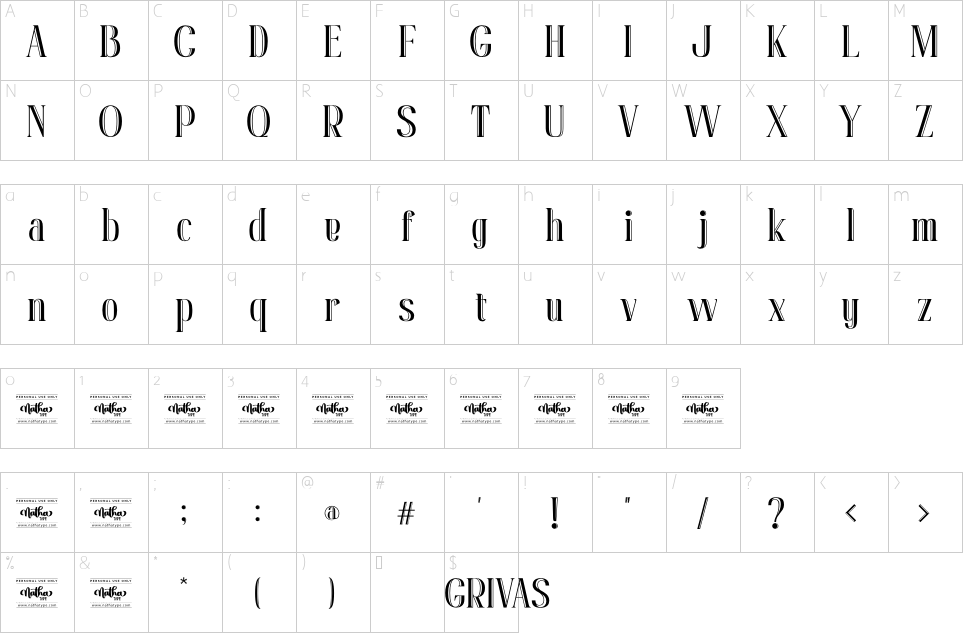
A Grivas Font é uma opção elegante para quem busca uma fonte de graça para projetos digitais. Desenvolvida pelo designer Natha Type, esta font foi amplamente utilizada e tem sido baixada mais de 807 vezes por designers que valorizam a beleza e o conforto do tipo em suas criações. Com seu design minimalista e moderno, Grivas se destaca como uma opção confiável para aplicativos web e desktop, emails personalizados e qualquer projeto que exige um toque de sofisticação. Aproveite esta fonte gratuita para expressar sua criatividade de maneira única e bem estilizada.